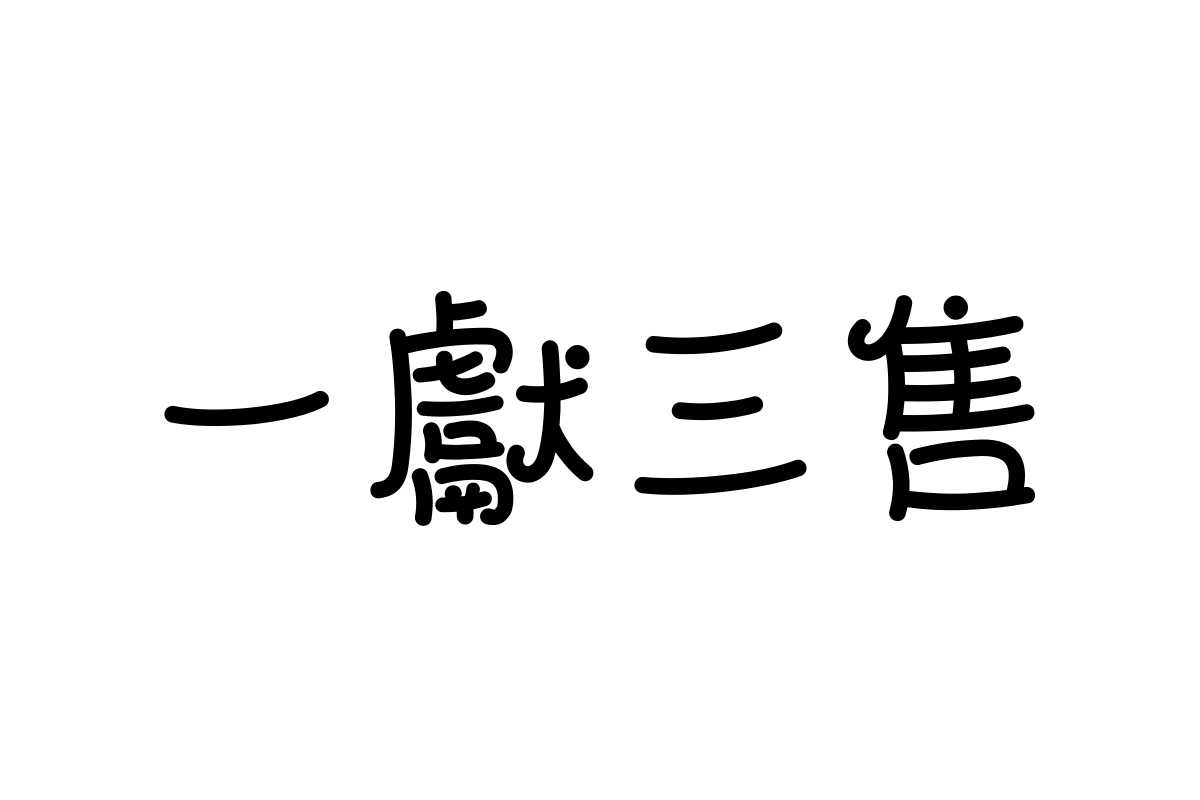
汉仪铸字扭扭薯条繁体版是一款由汉仪公司推出的中文字体。这款字体具有独特的设计,线条流畅,形状独特,给人一种新颖的感觉。它的笔画粗细适中,既有力度又不失柔美,适合用于各种需要展示文字的场合。同时,这款字体也具有较高的识别度,能够很好地表达出作者的个性和风格。
总的来说,汉仪铸字扭扭薯条繁体版是一款非常实用的字体,无论是在网页设计、广告设计还是其他任何需要展示文字的场合,都值得尝试使用。